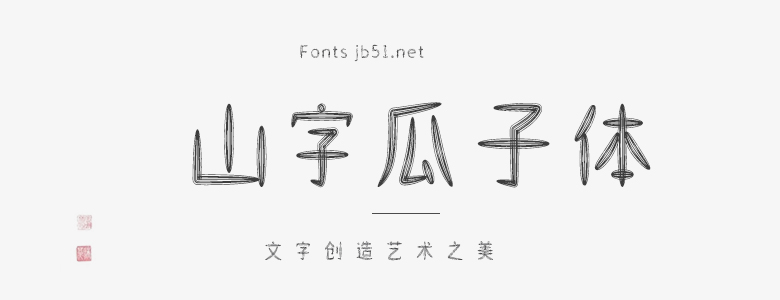
經(jīng)過(guò)漫長(zhǎng)的制作過(guò)程,山字瓜子體終于上線(xiàn)了。字庫(kù)含6763個(gè)常用中文字以及若干英文常用字母和標(biāo)點(diǎn)符號(hào)。由于筆畫(huà)形似瓜子,故取名瓜子體。也因?yàn)樗霉P畫(huà)是常規(guī)字庫(kù)的數(shù)倍,字庫(kù)也比常規(guī)簡(jiǎn)單筆畫(huà)的字庫(kù)要大許多。
該字庫(kù)適合廣告設(shè)計(jì)中需要用到可愛(ài)或卡通的字體的時(shí)候,適合用大字體來(lái)顯示,并不適合用小字(如四號(hào)等)來(lái)顯示。